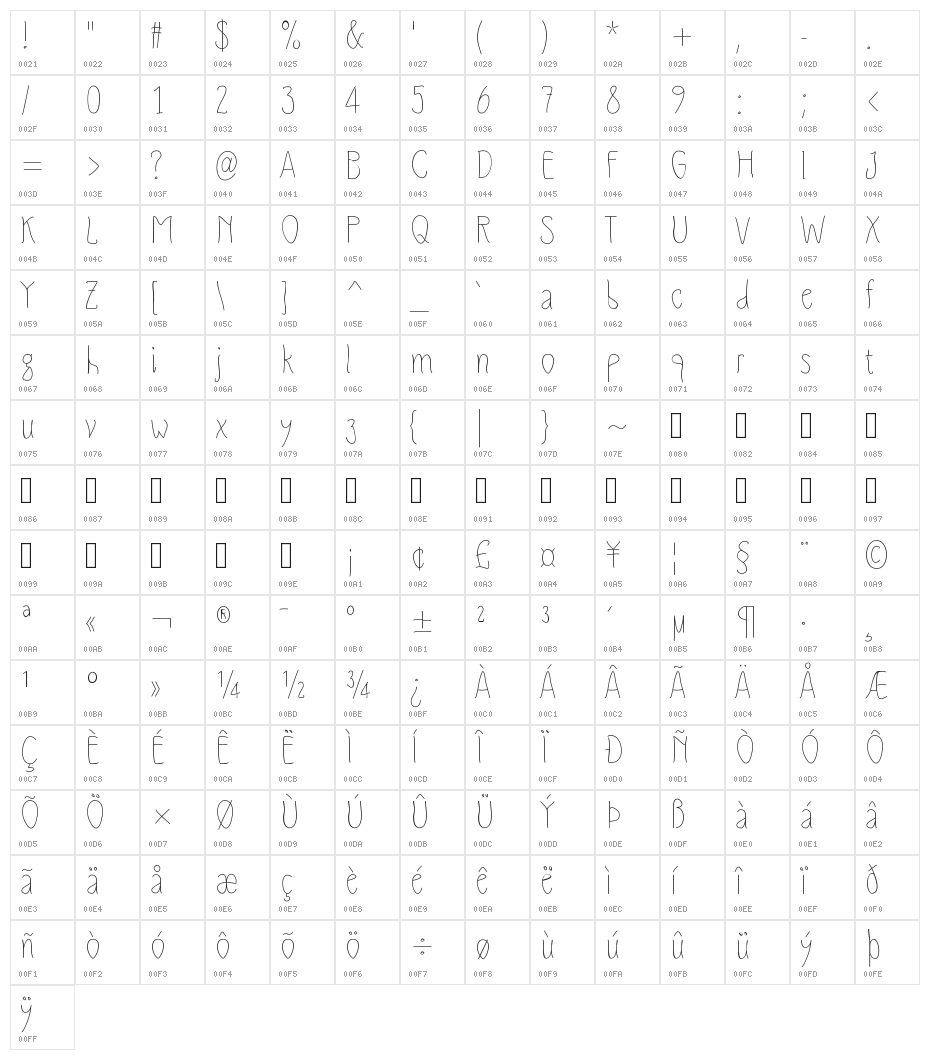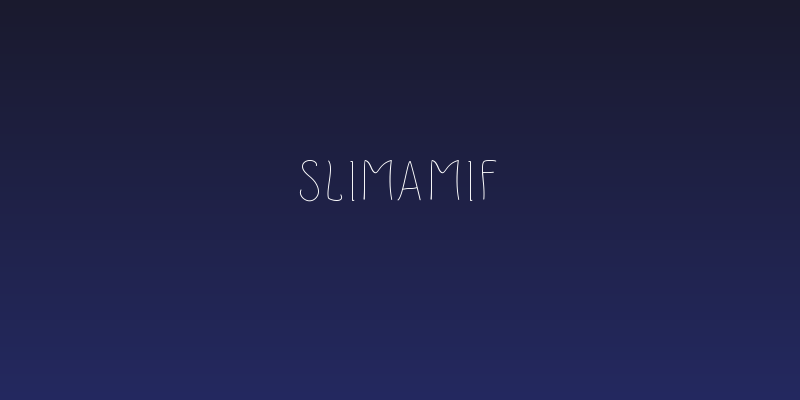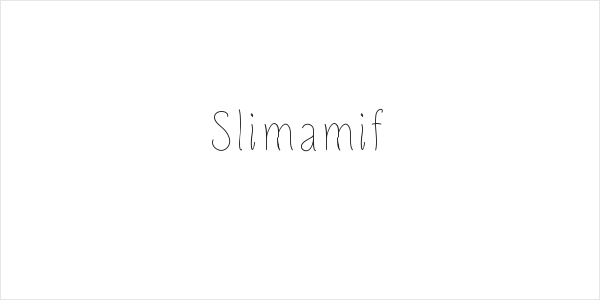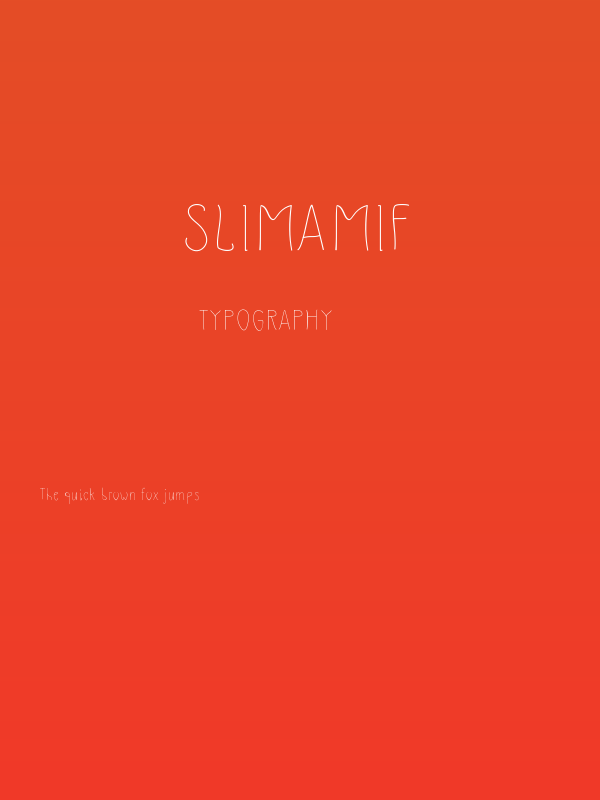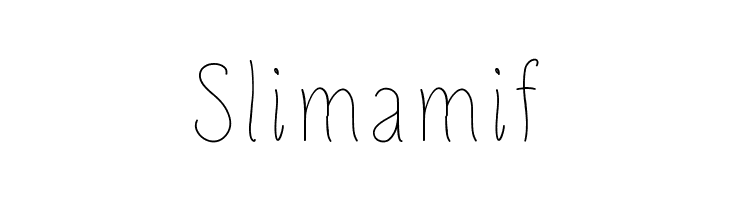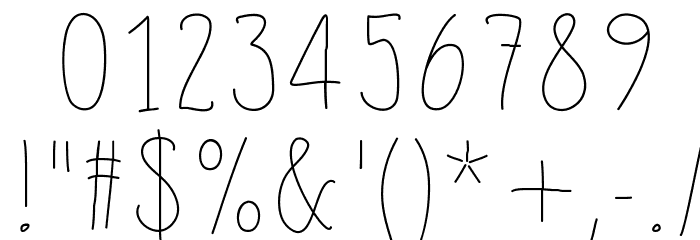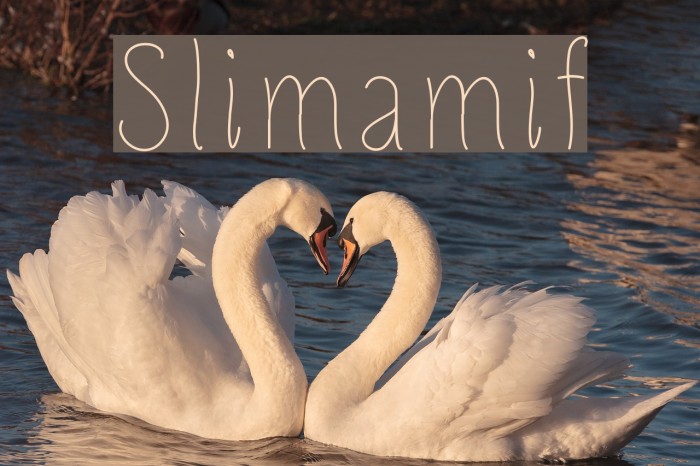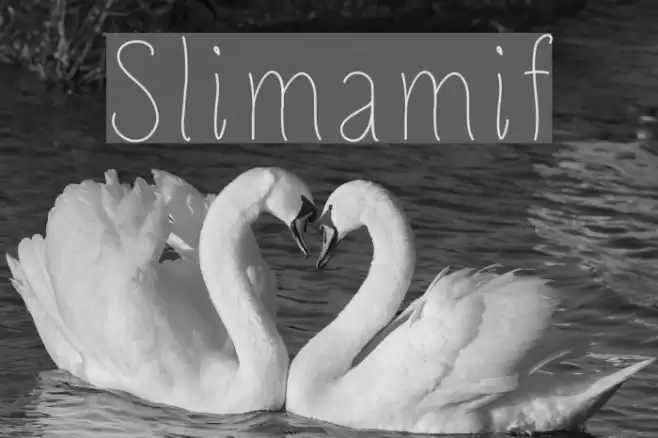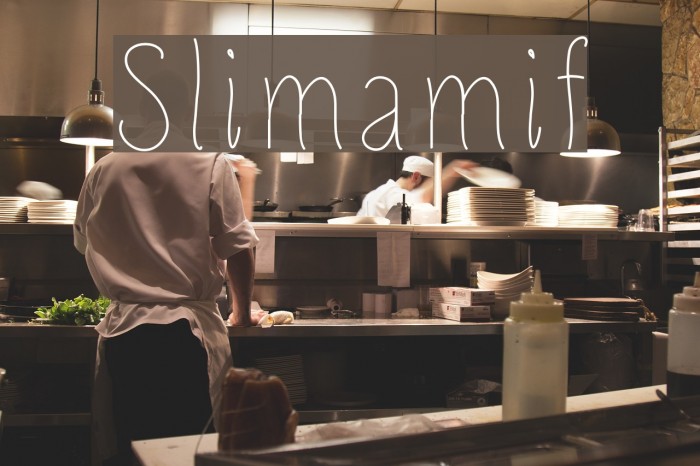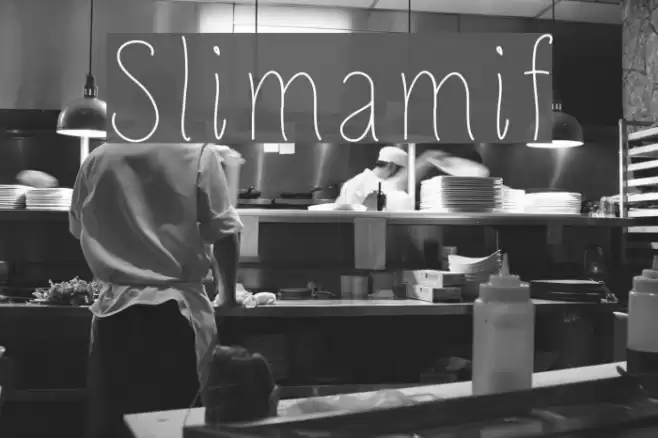
Slimamif Font
| Gesamtstil | Casual, Playful |
| Anwendungsfall | Headlines, Invitations, Creative projects |
| Vorgeschlagene Projekte | Ideal for greeting cards, children's books, playful branding, and casual invitations. |